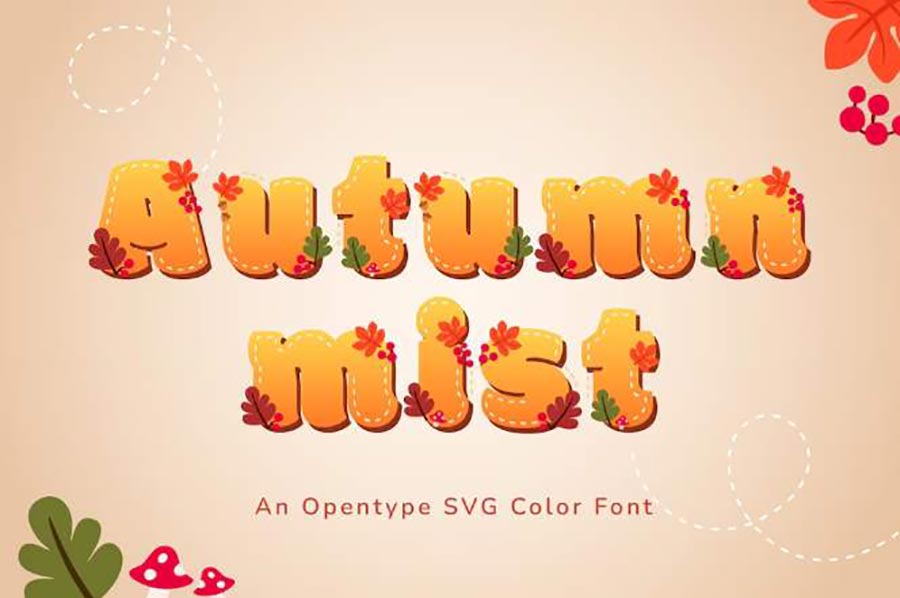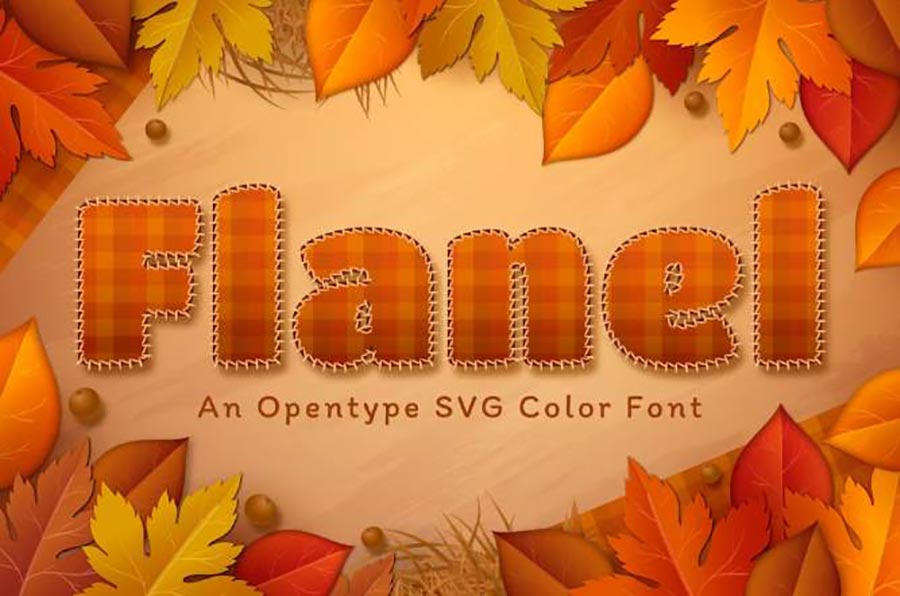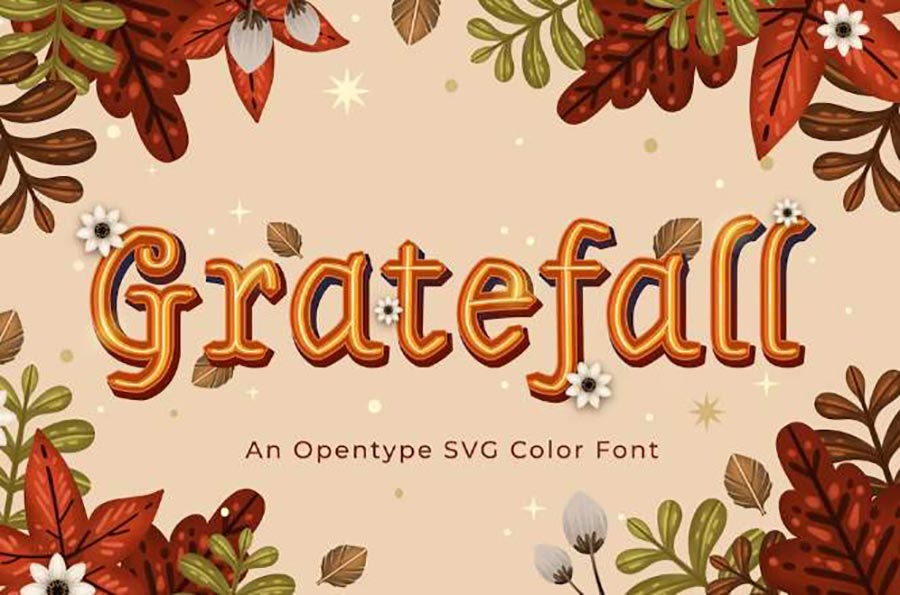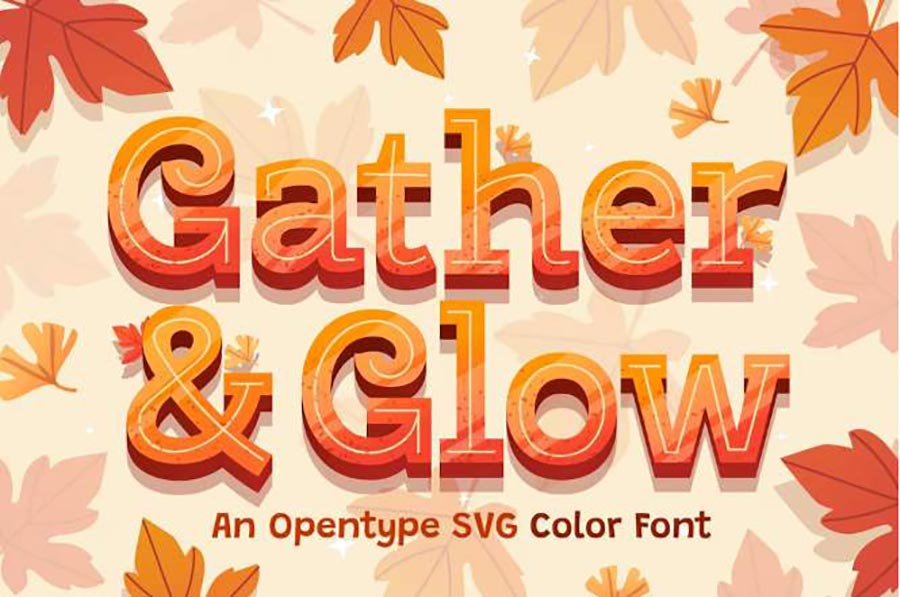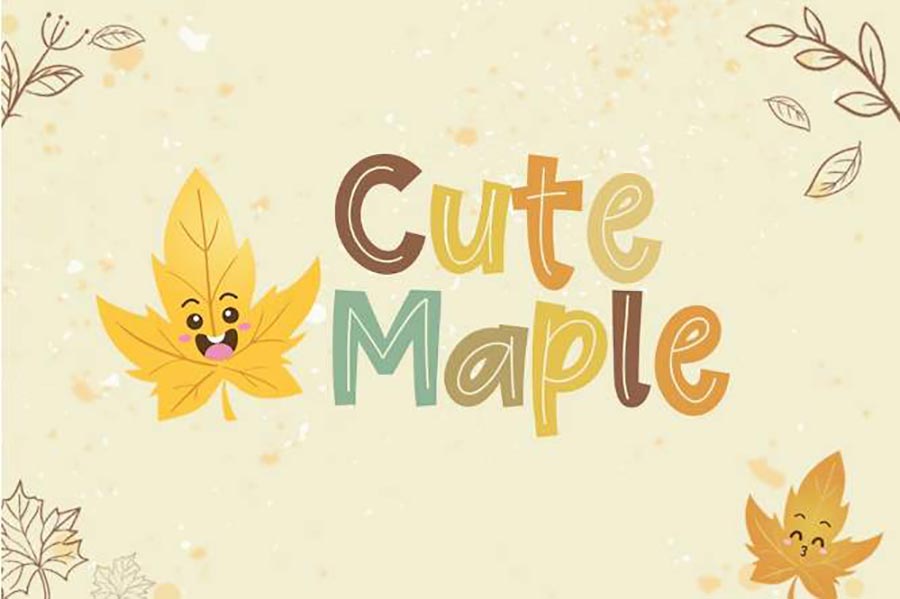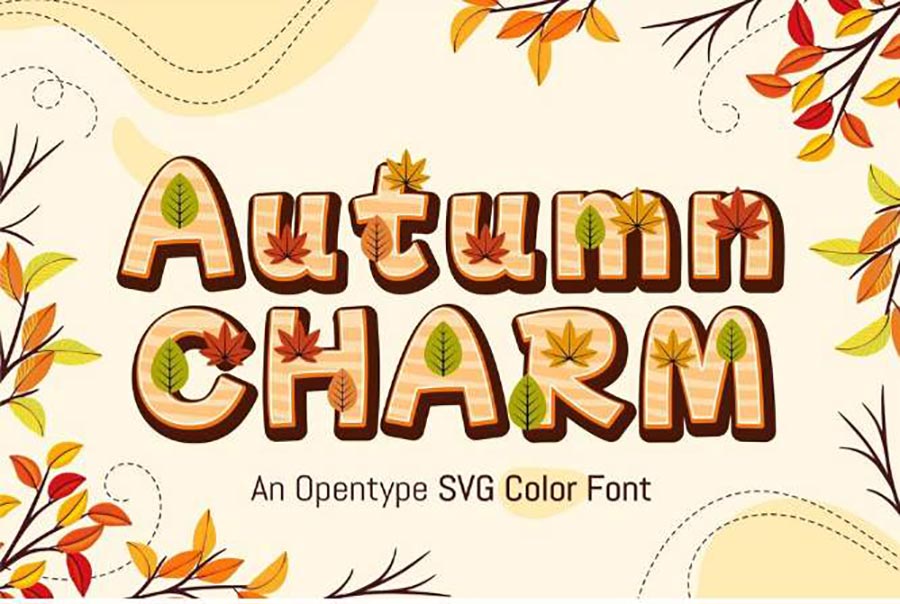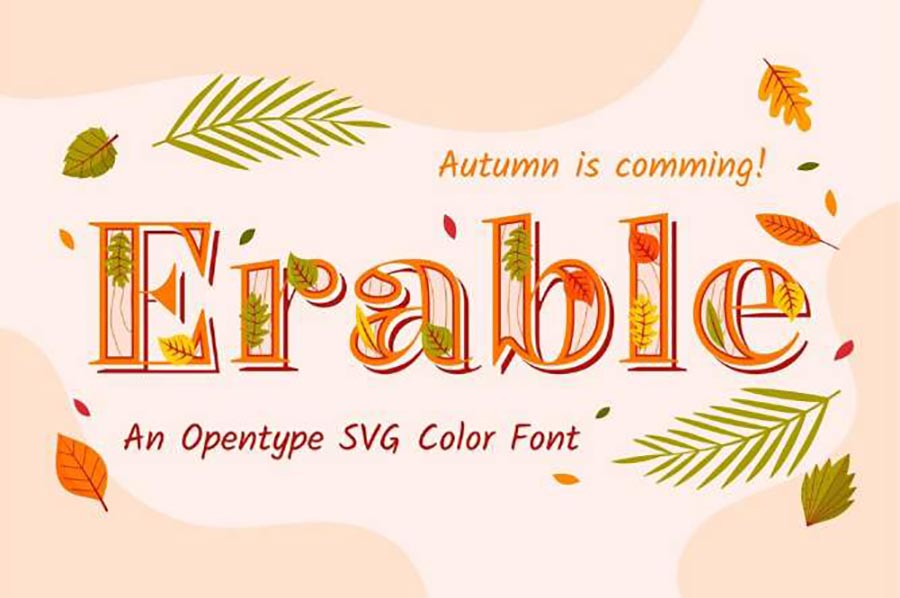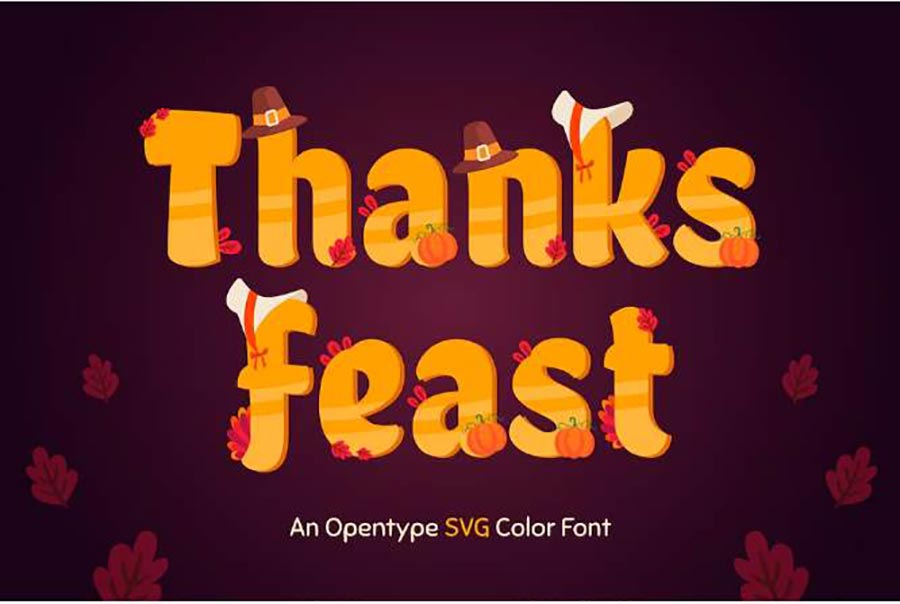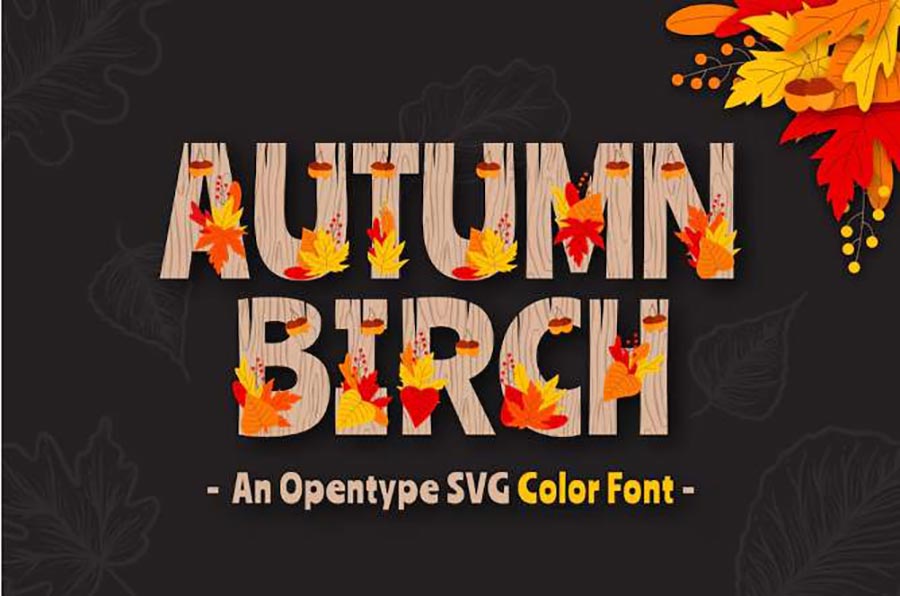
Chia Sẻ Bộ Font Chữ Mùa Thu Tuyệt Đẹp Miễn Phí
Mùa thu luôn mang lại một cảm giác ấm áp, nhẹ nhàng và lãng mạn. Đây là thời điểm lý tưởng để sáng tạo những thiết kế mới mẻ, mang đậm sắc thu. Nếu bạn đang tìm kiếm những font chữ đẹp, phù hợp với không khí mùa thu để sử dụng cho các dự án thiết kế của mình, bộ font chữ mùa thu tuyệt đẹp miễn phí từ Sadesign.vn chính là lựa chọn hoàn hảo. Bộ sưu tập này sẽ giúp bạn thêm phần sáng tạo, mang lại vẻ đẹp tự nhiên và ấm cúng cho mỗi tác phẩm.
Lý Do Nên Chọn Font Chữ Mùa Thu
Font chữ không chỉ là một công cụ để truyền tải thông điệp, mà còn đóng vai trò quan trọng trong việc tạo nên vẻ đẹp và ấn tượng cho các thiết kế. Đặc biệt, đối với mùa thu – một mùa của sự tĩnh lặng, dịu dàng và lãng mạn – việc chọn lựa những font chữ phù hợp sẽ giúp tôn lên không khí đặc trưng của mùa này.
Bộ font chữ mùa thu từ Sadesign.vn mang lại sự hài hòa giữa nét cổ điển và hiện đại. Các font này thường có sự kết hợp giữa những đường nét mềm mại, uốn lượn nhẹ nhàng cùng các chi tiết tươi sáng, mộc mạc, phù hợp cho những thiết kế từ thiệp mời, poster đến các bài đăng trên mạng xã hội. Những font chữ này sẽ giúp tạo ra không gian ấm áp, dễ chịu, đồng thời cũng không kém phần sang trọng và độc đáo.
Bộ Font Chữ Mùa Thu Miễn Phí Từ Sadesign.vn
Bộ font chữ mùa thu từ Sadesign.vn không chỉ đa dạng về kiểu dáng mà còn rất dễ sử dụng. Dưới đây là một số điểm nổi bật của bộ font này:
Font Chữ Mềm Mại Và Lãng Mạn
Những font chữ mềm mại, uốn lượn như thể phản ánh không khí nhẹ nhàng của mùa thu. Các chữ cái được thiết kế với những nét thanh mảnh, uyển chuyển, giúp thể hiện được sự lãng mạn và dịu dàng. Đây là lựa chọn lý tưởng cho các thiệp mời, các bài viết trên blog, hoặc các chiến dịch truyền thông mùa thu.
Font Chữ Đậm Và Mạnh Mẽ
Ngoài những font mềm mại, bộ font chữ mùa thu này cũng bao gồm các kiểu chữ đậm, mạnh mẽ, với những nét chữ góc cạnh và chắc chắn. Những font này mang lại cảm giác đầy năng lượng và hiện đại, phù hợp với các thiết kế quảng cáo hoặc các dự án sáng tạo có tính năng động cao.
Font Chữ Với Chi Tiết Trang Trí
Một số font trong bộ sưu tập này còn có các chi tiết trang trí nhẹ nhàng như các họa tiết lá rơi, hoa cúc, hoặc các hình ảnh đặc trưng của mùa thu. Những chi tiết này sẽ làm cho các thiết kế trở nên sinh động hơn, đồng thời tạo ra không gian gần gũi và ấm áp, rất thích hợp cho các thiệp chúc mừng hoặc các bài viết liên quan đến mùa thu.